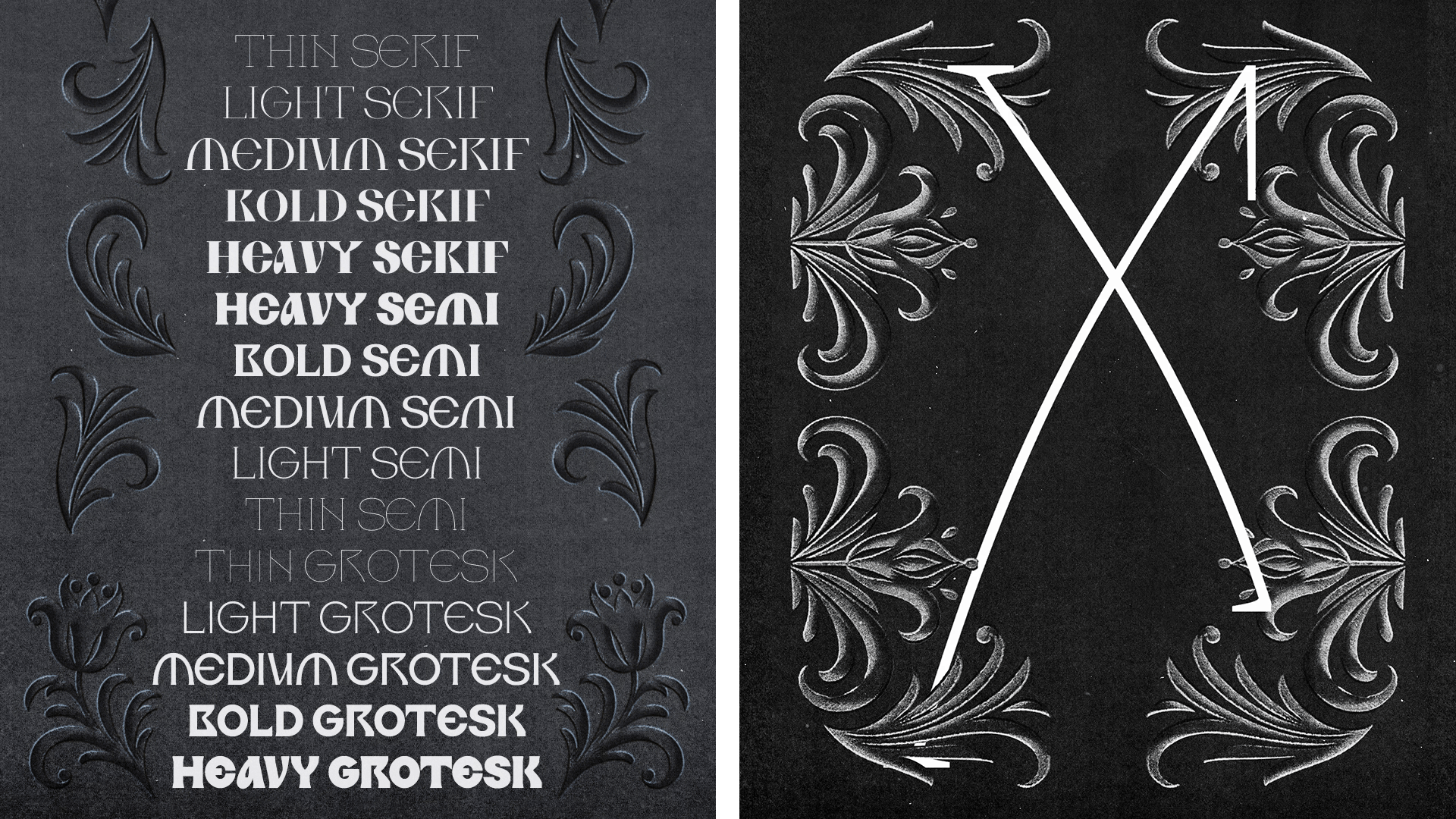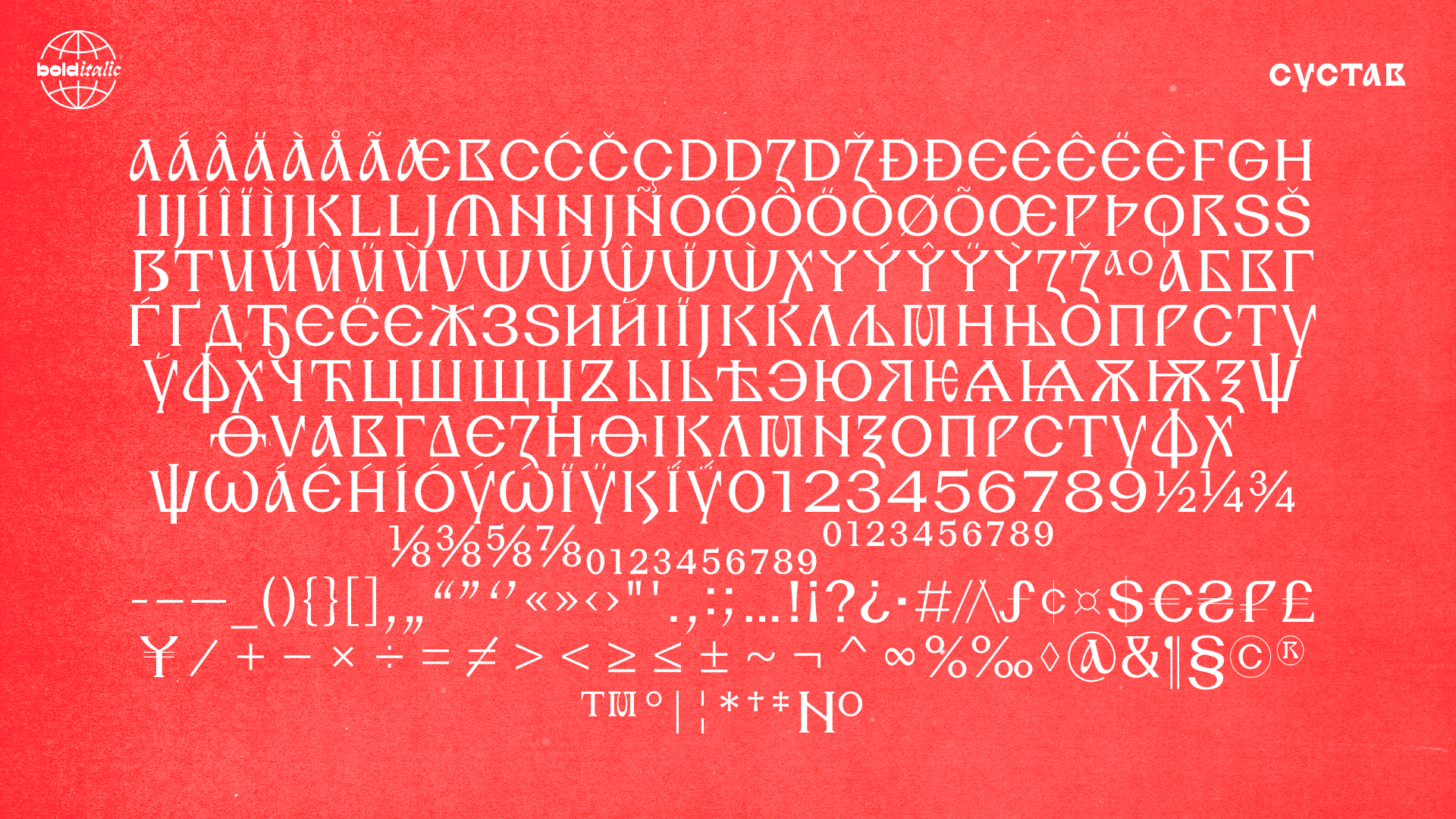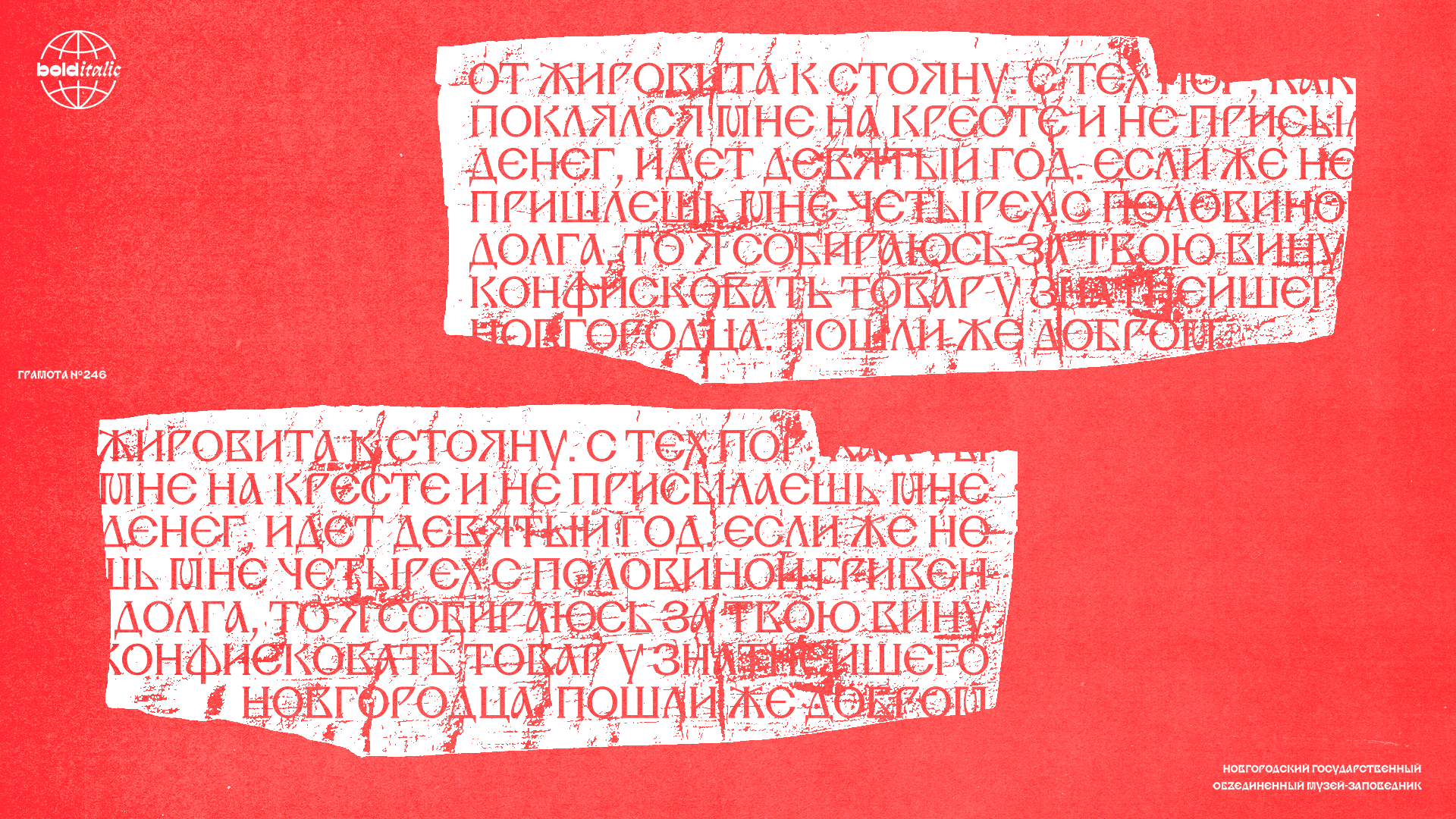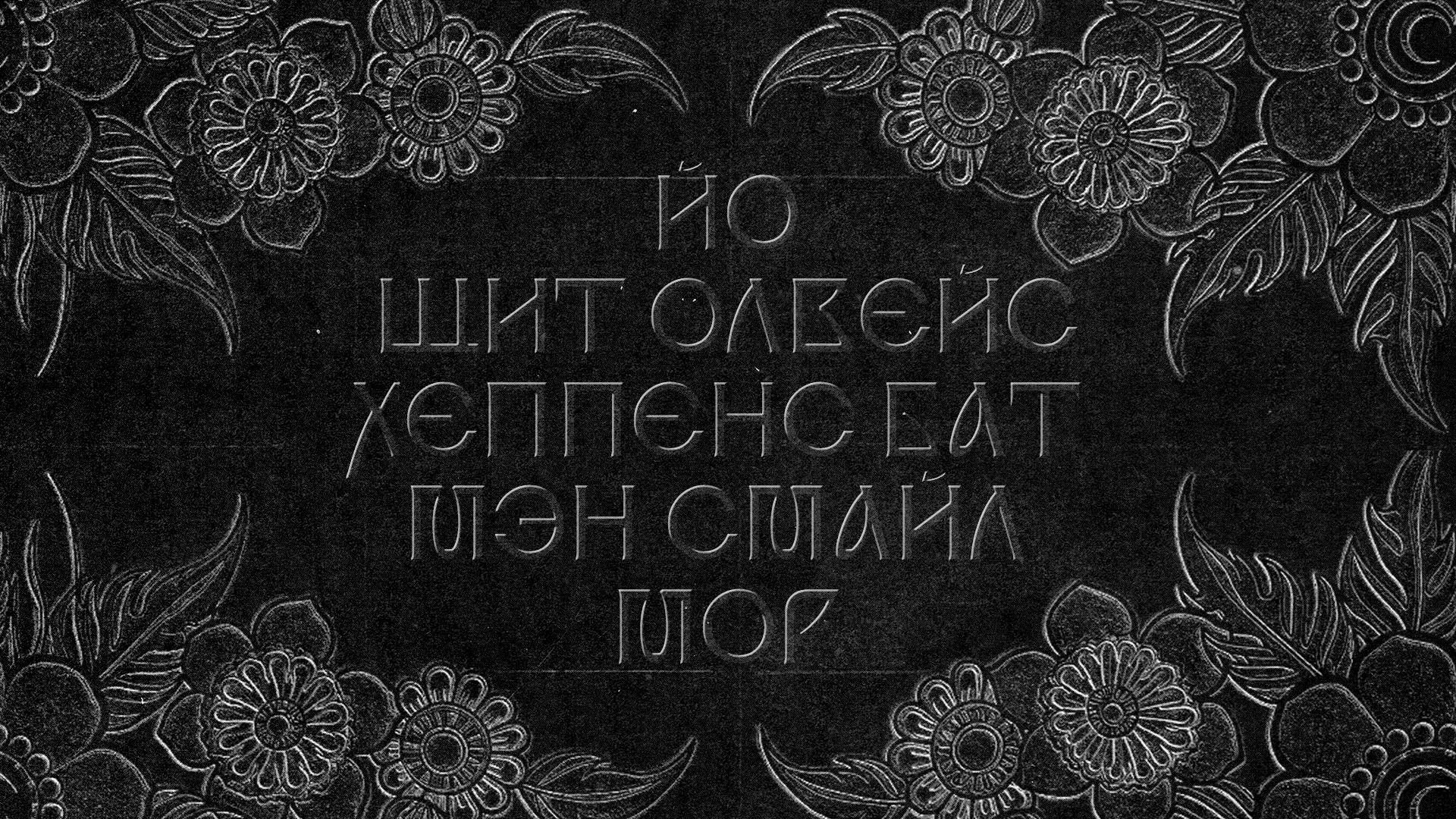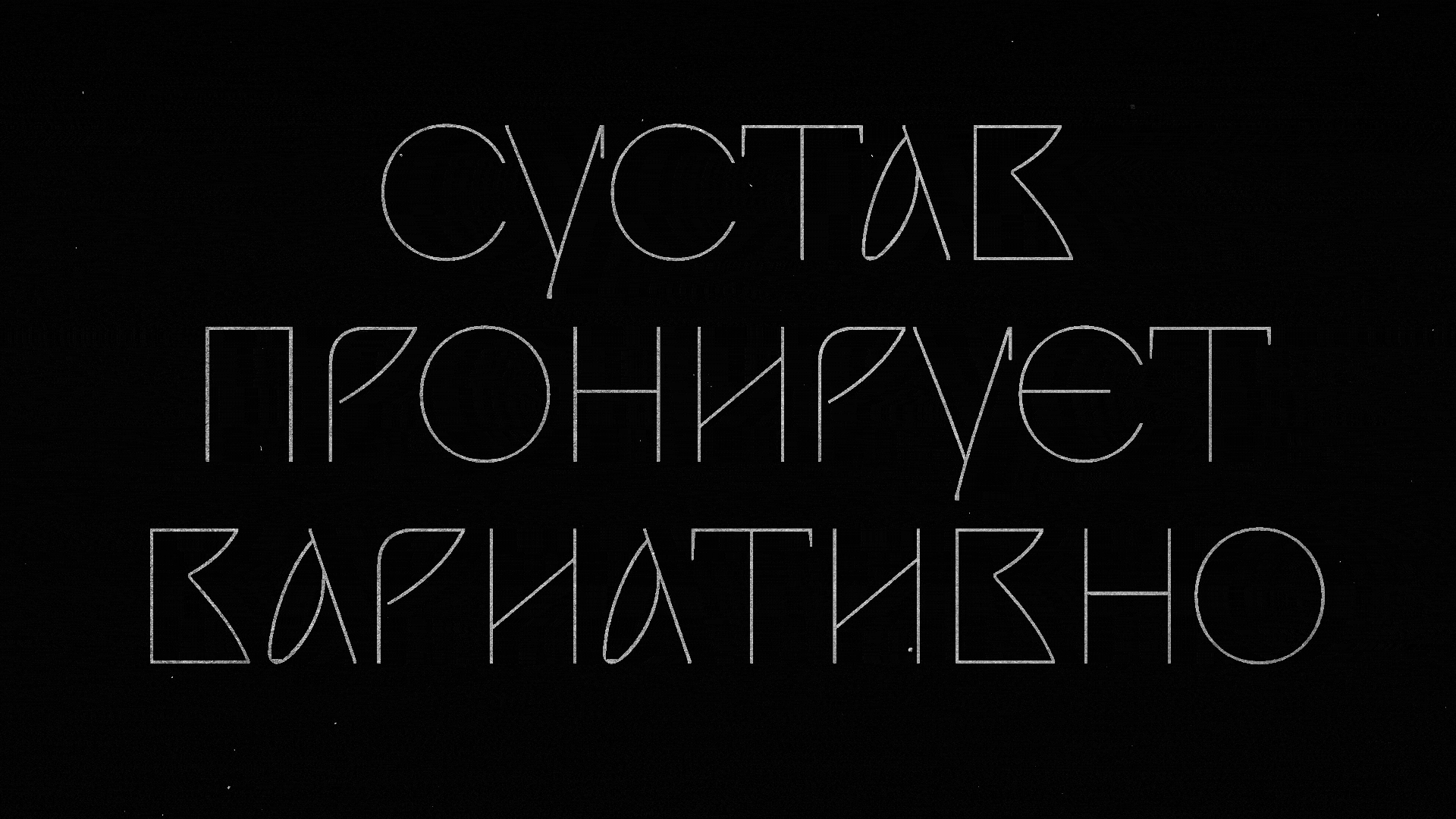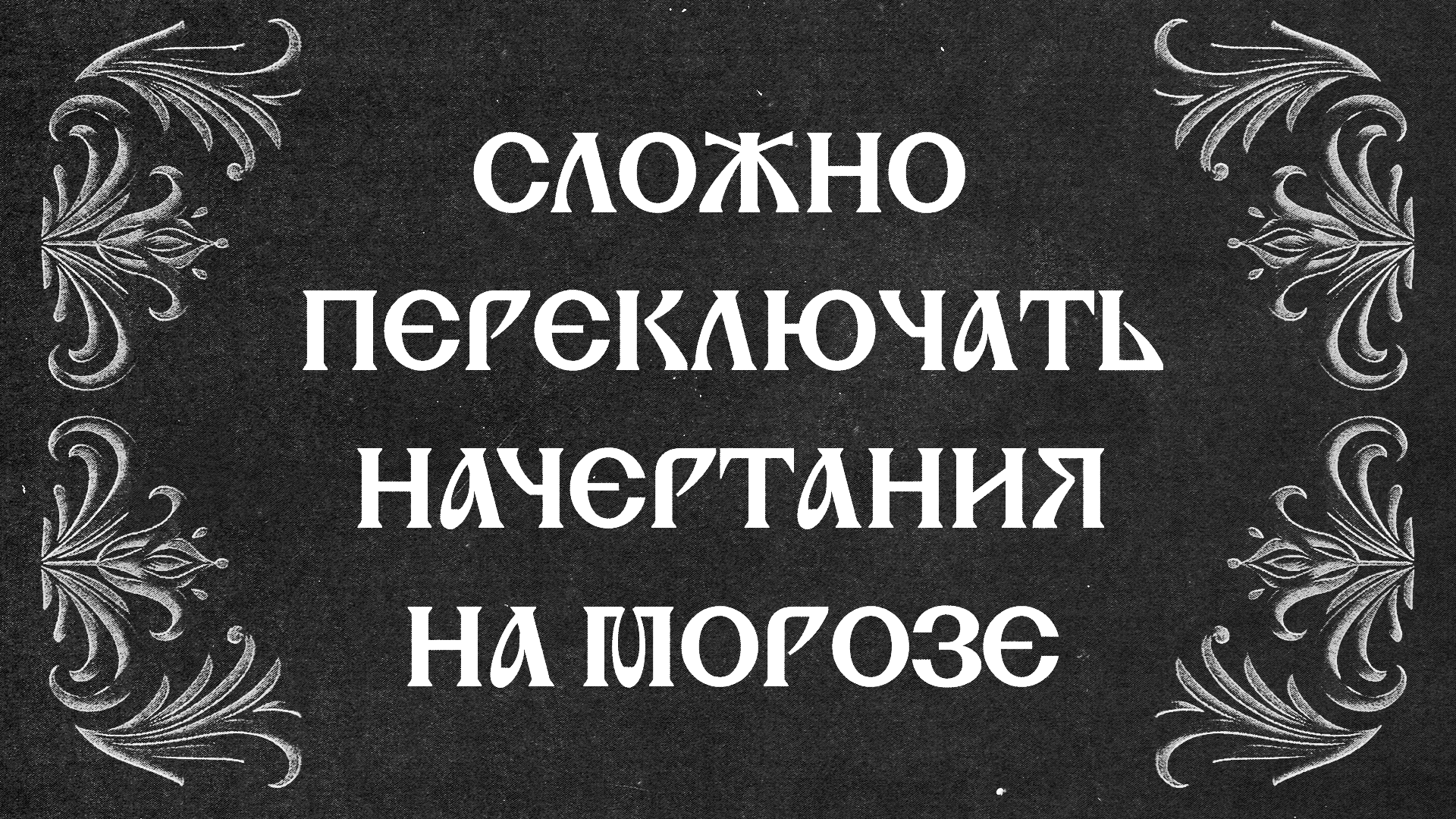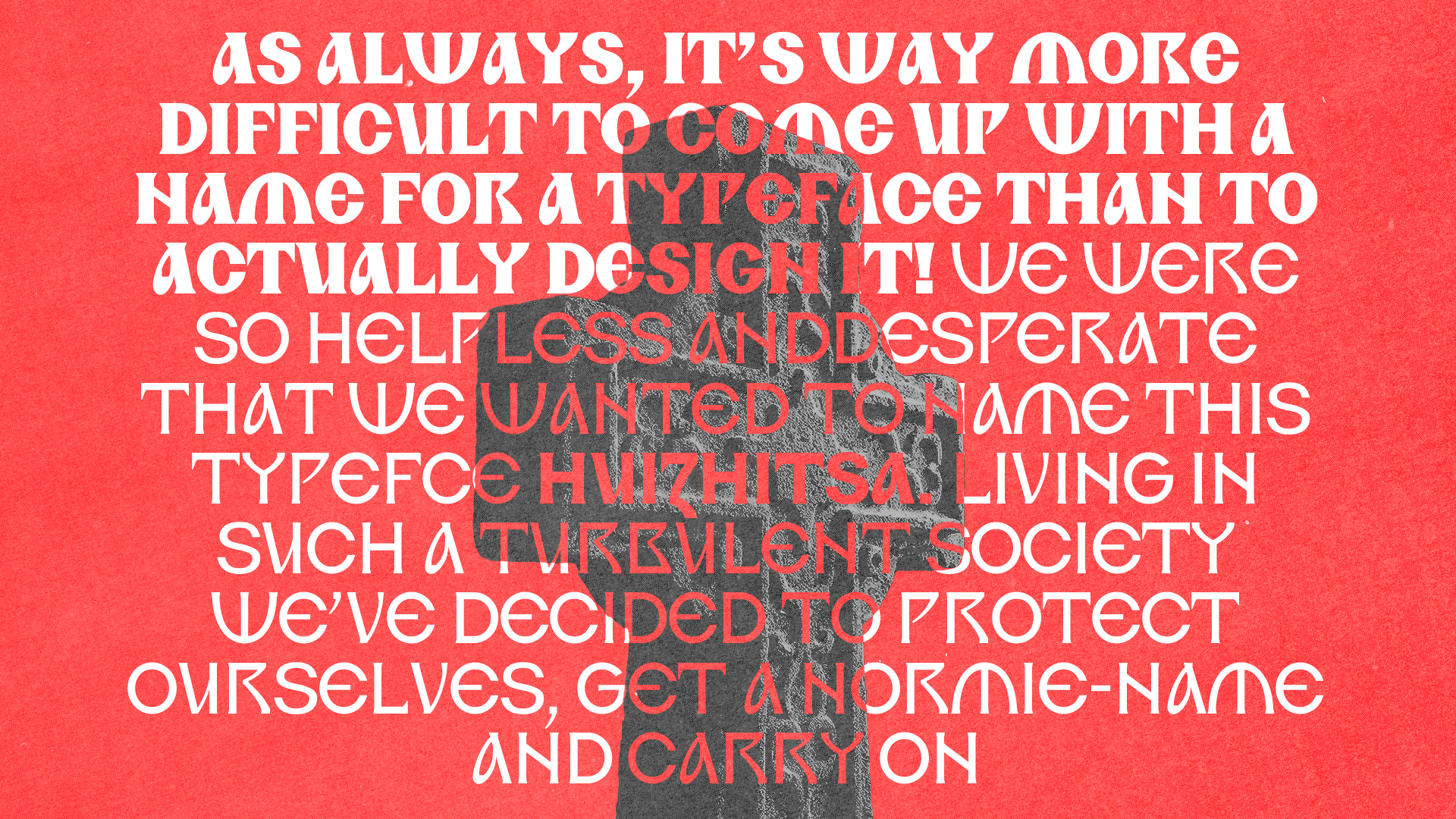
Тиражный шрифт
Sustav
Хулиганский отвар из букв, выполненный по допетровским рецептам на современном оборудовании.
Сустав хорошо гнется по двум осям: контраст и насыщенность, но содержит только один регистр!
Знаковый состав поддерживает славянские кириллические языки, а также языки западной Европы.